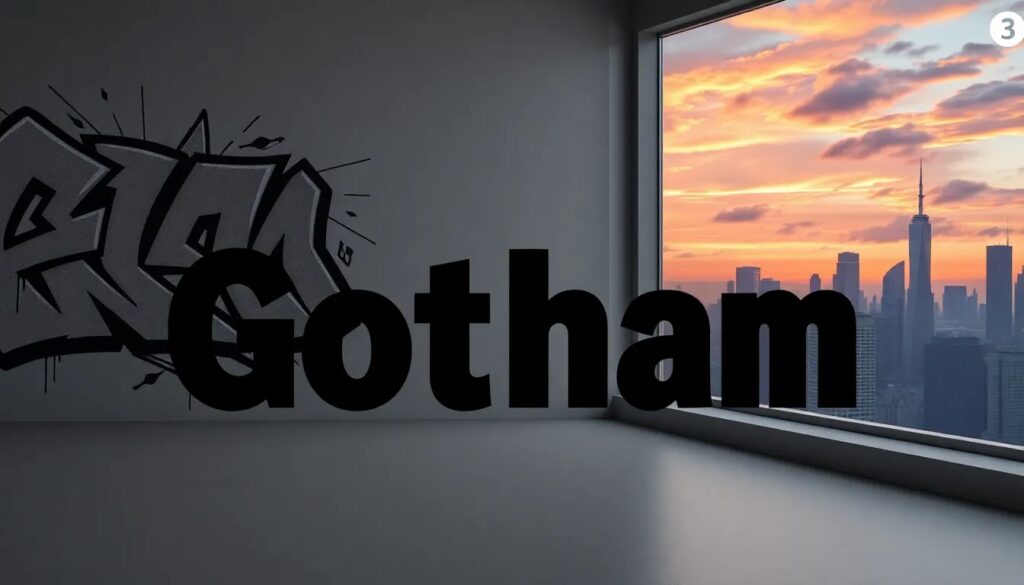
Gotham google font y sus alternativas gratuitas
La tipografía juega un papel crucial en el diseño gráfico y la comunicación visual. Dentro de este campo, la Gotham Google Font destaca como una de las fuentes más reconocibles y utilizadas. Creada por Tobias Frere-Jones, esta tipografía sans-serif geométrica ha dejado una huella significativa en proyectos de renombre, desde campañas políticas hasta diseños editoriales. En este artículo, exploraremos las alternativas a Gotham que se pueden encontrar en Google Fonts, analizando sus características y ventajas.
Google Fonts similar a Gotham
Gotham se ha consolidado como una fuente emblemática, pero no siempre se encuentra disponible. Afortunadamente, existen alternativas similares en Google Fonts que ofrecen características parecidas.
Entre las fuentes más destacadas, encontramos a Raleway, que ofrece un estilo elegante y moderno. Otra opción es Montserrat, la cual ha ganado popularidad por su versatilidad en aplicaciones web.
- Raleway: presenta una estética delgada y estilizada.
- Montserrat: ofrece una mayor diversidad de pesos, lo que permite un uso flexible.
- Open Sans: es conocida por su excelente legibilidad en pantallas.
Estas fuentes no solo son similares en apariencia, sino que también son gratuitas y se pueden utilizar fácilmente en proyectos de diseño gráfico.
¿Qué Google Fonts son similares a Gotham?
Cuando se busca una fuente que se asemeje a Gotham, es esencial considerar varias opciones. Raleway y Montserrat son las más comunes, pero también existen otras como Geomanist y Metropolis.
La comparación de estos tipos nos ayuda a entender mejor sus aplicaciones. Por ejemplo, Metropolis se caracteriza por su similitud en el grosor de las letras y ofrece hasta nueve pesos diferentes, lo que la convierte en una excelente opción para aquellos que buscan versatilidad.
- Raleway: ideal para diseños minimalistas.
- Montserrat: popular en sitios web y branding.
- Geomanist: destaca por su estilo geométrico.
Estas alternativas permiten mantener un estilo profesional en el diseño, sin necesidad de adquirir licencias costosas.
¿Cuáles son las alternativas gratuitas a Gotham?
Para quienes buscan opciones sin costo, las alternativas a Gotham Google Font son numerosas. Estas fuentes no solo son estéticamente agradables, sino que también ofrecen un buen rendimiento en la web.
Entre las cinco mejores opciones gratuitas se encuentran:
- Metropolis: su diseño se asemeja mucho al de Gotham, con una variedad de estilos.
- Figtree: creada por el mismo autor, comparte características similares y es altamente versátil.
- Montserrat: ampliamente utilizada, ofrece un estilo contemporáneo.
- Raleway: se puede ajustar para parecer más cercana a Gotham.
- Geomanist: presenta un estilo geométrico atractivo.
Estas fuentes son perfectas para quienes desean un diseño gráfico profesional sin el gasto asociado.
¿Qué tipografías son recomendadas como alternativas a Gotham?
Las tipografías recomendadas como alternativas a Gotham suelen compartir elementos de diseño que las hacen atractivas para el mismo tipo de aplicaciones. Raleway y Open Sans son dos de las más mencionadas por su legibilidad y estilo moderno.
Además, es importante considerar el contexto en el que se utilizará la fuente. Por ejemplo, Open Sans es ideal para textos largos y párrafos, mientras que Raleway puede ser más adecuada para títulos y encabezados.
Al seleccionar la tipografía, se deben tener en cuenta aspectos como:
- Legibilidad: asegurarse de que el texto sea fácil de leer.
- Estilo: la tipografía debe ajustarse al tono del proyecto.
- Versatilidad: la posibilidad de usar diferentes pesos y estilos.
¿Cuáles son las mejores fuentes gratuitas en Google Fonts?
Al explorar las mejores fuentes gratuitas en Google Fonts, es fundamental fijarse en la Gotham Google Font como un punto de referencia. Las opciones como Montserrat y Raleway ofrecen características que se asemejan a Gotham, proporcionando alternativas viables.
Otras fuentes destacables incluyen:
- Metropolis: conocida por su elegancia y variedad en pesos.
- Figtree: busca un equilibrio entre estilo y funcionalidad.
- Geomanist: ideal para proyectos que requieren un toque geométrico.
Estas fuentes son altamente recomendadas por su calidad y disponibilidad en Google Fonts, permitiendo a los diseñadores gráficos acceder a opciones profesionales sin costo.
En conclusión, la elección de la fuente debe basarse en el propósito del diseño y el público objetivo. Las tipografías juegan un papel fundamental en la comunicación visual, y elegir correctamente puede elevar la calidad de cualquier proyecto.